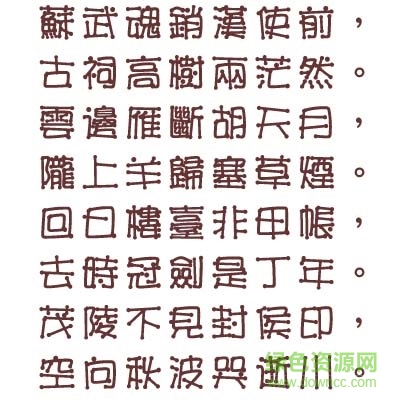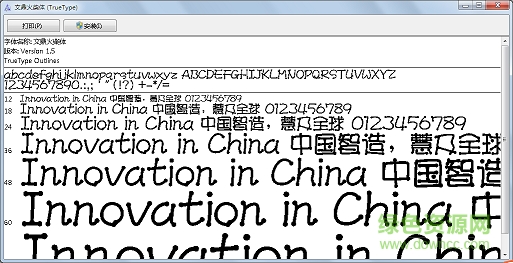
文鼎火柴體字體
文鼎火柴體是一款特色非常鮮明中文簡(jiǎn)體字,每個(gè)筆畫(huà)的開(kāi)頭和結(jié)尾都有原點(diǎn),給人一種有始有終的感覺(jué),其字體的形式也非常的具有特色,也能讓你在聊天或者進(jìn)行書(shū)面排版時(shí)字體變得更加炫酷哦,感興趣的朋友歡迎來(lái)綠色資源網(wǎng)下載哦。
字體簡(jiǎn)介
字體融入夢(mèng)境般的風(fēng)波卷元素,裝飾味十足,充滿(mǎn)童趣。以俏皮多變的線(xiàn)條,造就一款蘊(yùn)含童真、童夢(mèng)的字體。讓我們乘著童年的時(shí)光機(jī),進(jìn)入奇妙的夢(mèng)幻之旅,遇見(jiàn)一場(chǎng)奇緣!